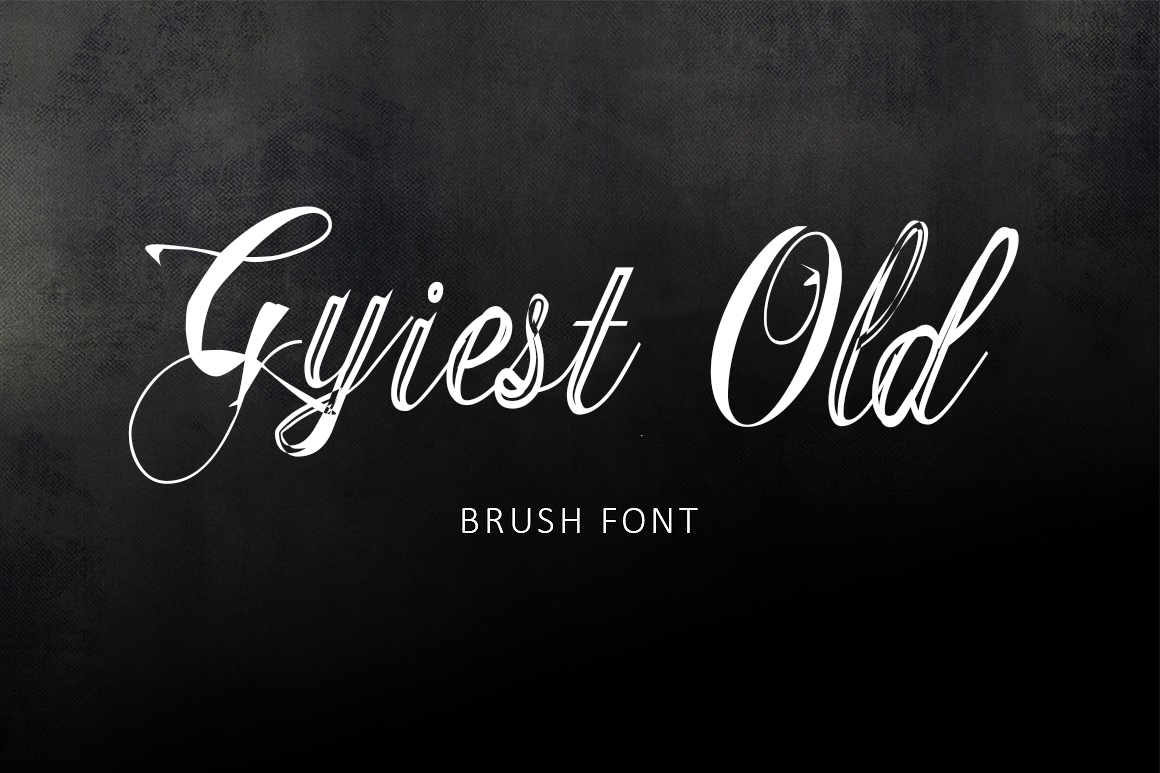
Gyiest Old Brush Font – Download Grátis
Olá! A gente está muito animado com a novidade que tem pra vocês hoje: Gyiest Old. Esta fonte brush é uma criação genial do designer Hamilton e foi compartilhada por Malre. Gyiest Old traz um estilo de traço autêntico, ou seja, ele não é apenas uma fonte padrão, mas sim uma arte feita à mão que exala personalidade. Suas letras são belíssimas e sofisticadas ao mesmo tempo. Com este design encantador na sua coleção de fonts brush, você terá inúmeras possibilidades para usos incríveis! Gyiest Old é perfeito para criar um estilo único em aplicativos como Instagram ou no desenvolvimento de logotipos. Ele também está repleto de potencial para criações do tipo marketing e até mesmo para cartões de convite ou decoração de casamento. Tudo isso sem mencionar o uso incrível que você poderá fazer com Gyiest Old em eventos especiais, onde a personalização é chave para uma experiência memorável. Em resumo, Gyiest Old é um brinde da criatividade e é perfeito tanto para quem quer deixar seu design de primeira qualidade como para aqueles que estão procurando por uma maneira única de expressar suas ideias.